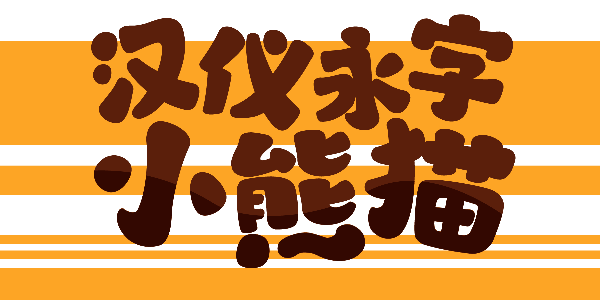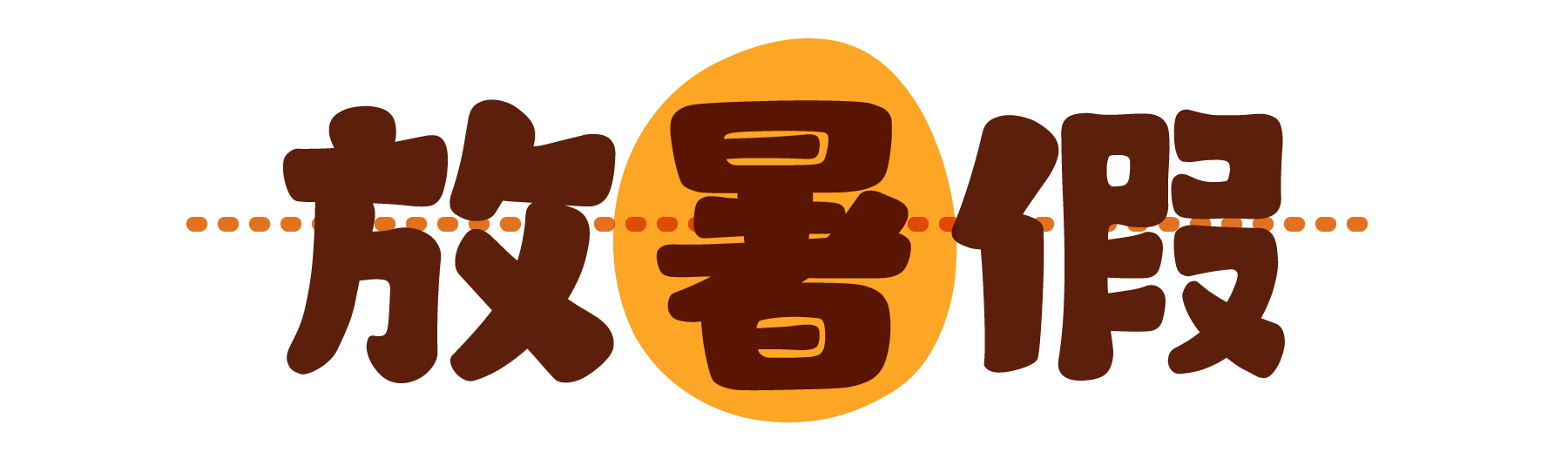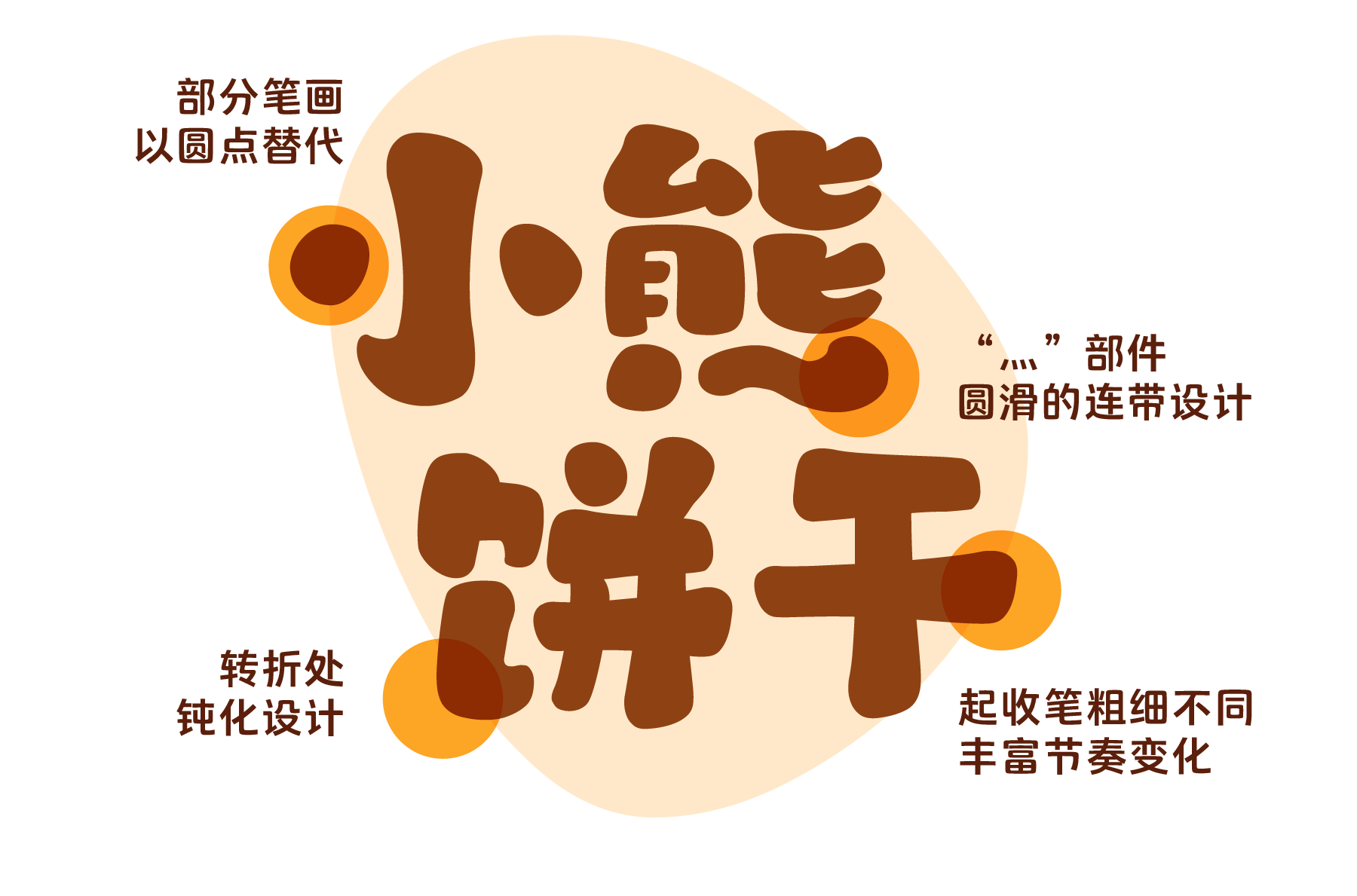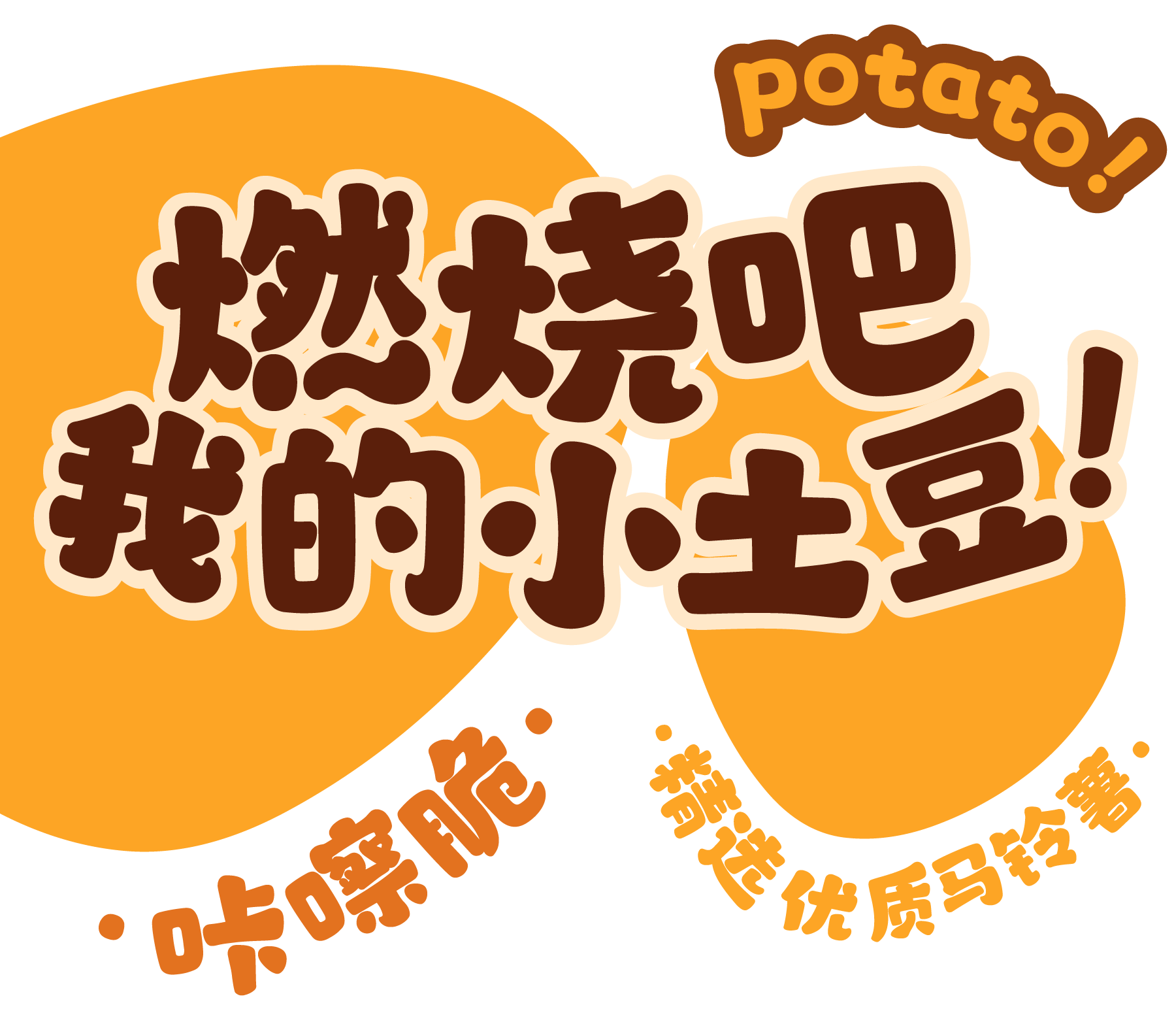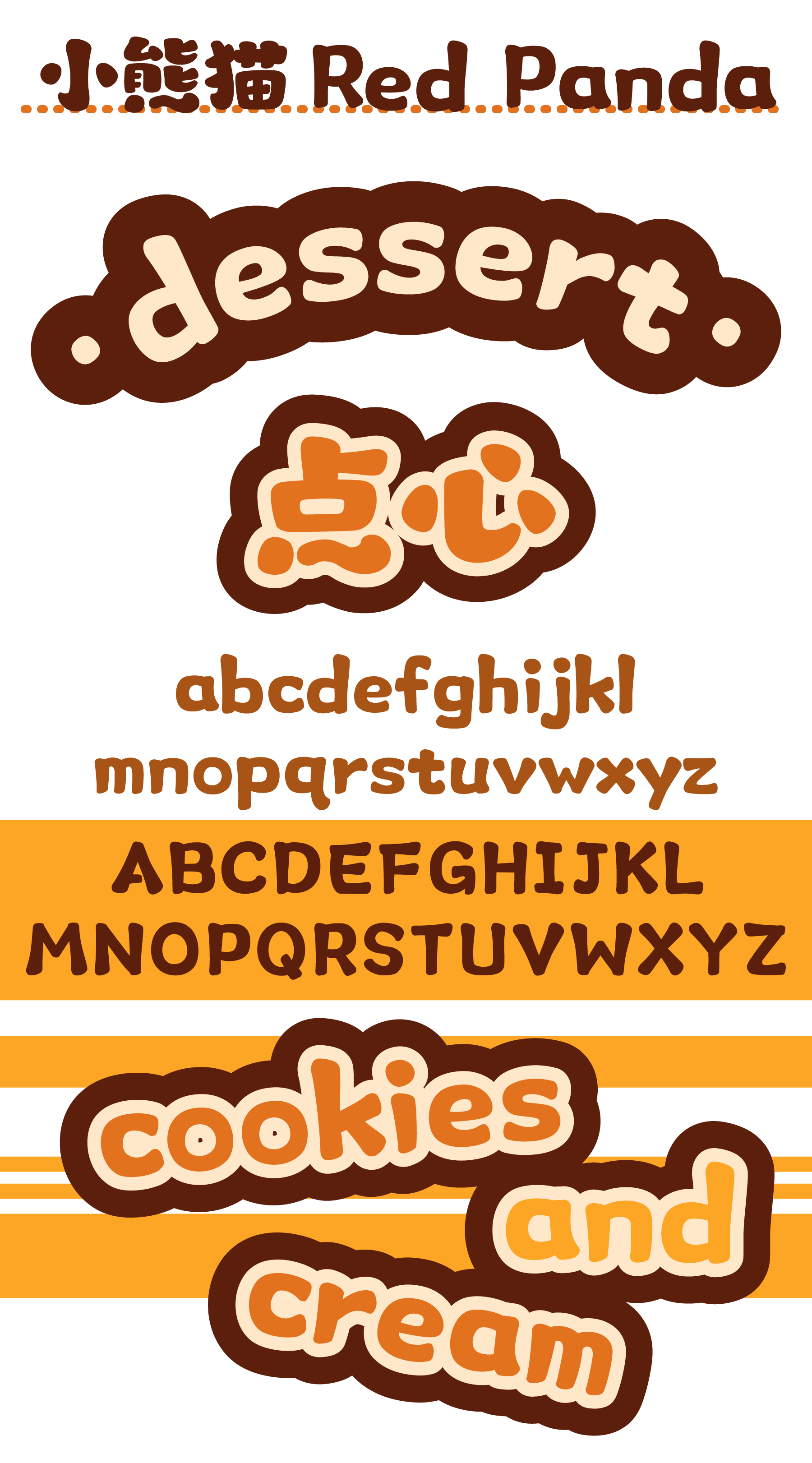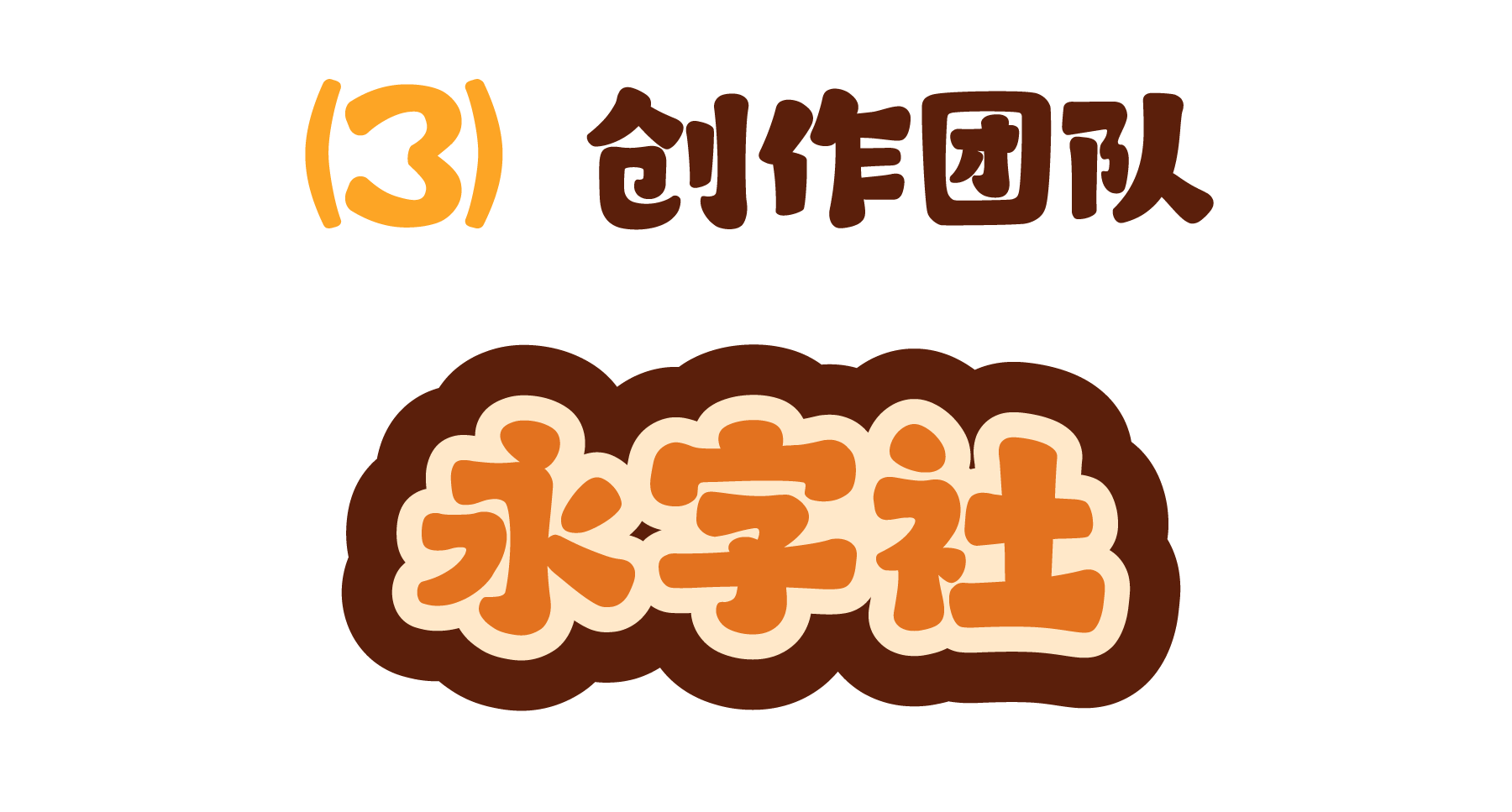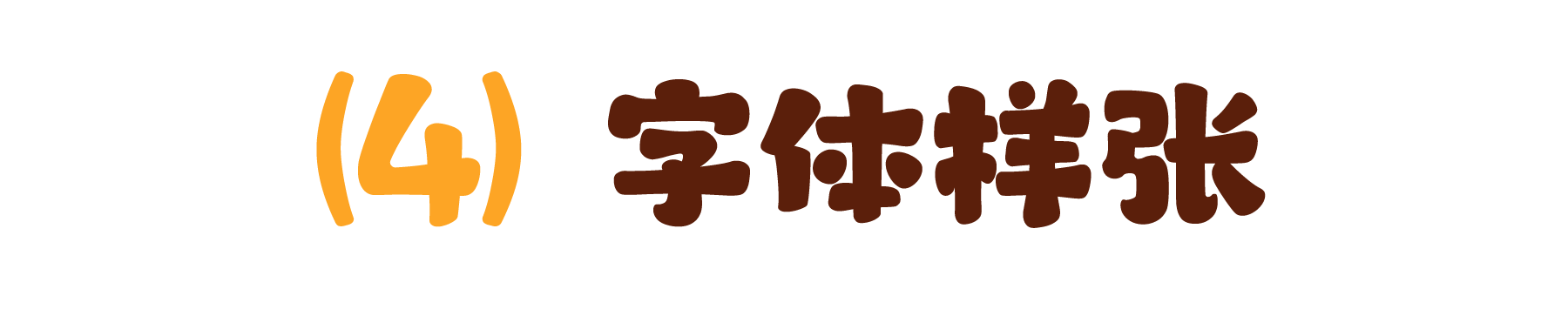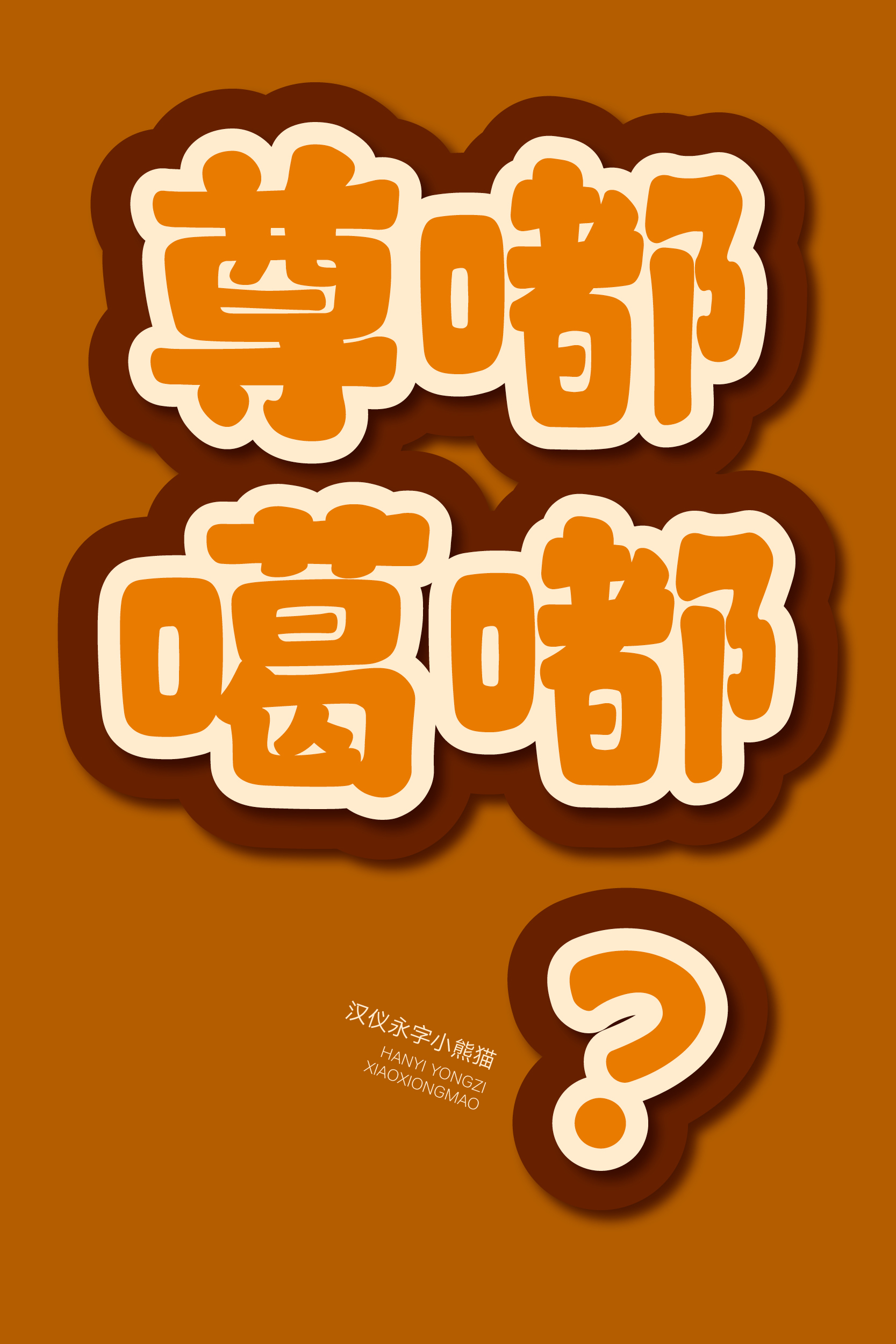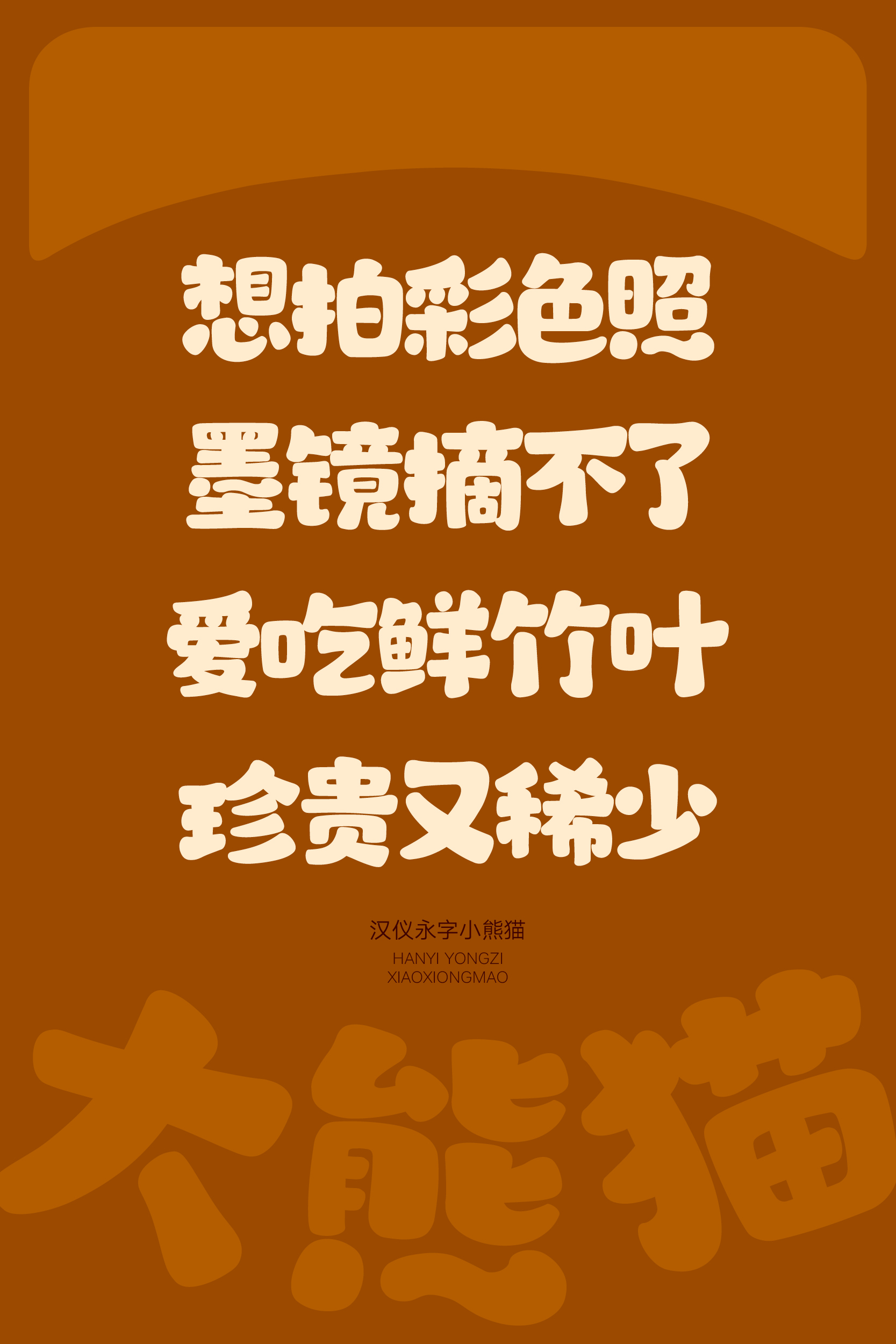
圆润可爱的小熊猫躲进字体里了
汉仪永字小熊猫,来自永字社的一款设计字体。字体整体圆润可爱,字面略小、饱满充实,圆头圆尾的笔画柔软有弹力,给人以轻松快乐的视觉体验。笔画有粗细变化,化方为圆,并加入一些圆滑的连带,自然稚拙,像是小熊猫用掌垫绘写而成。这款字体适合用于少儿科普、图书绘本、食品包装、休闲娱乐等使用场景,为排版创造可爱活泼、柔软温暖的氛围。
整体圆润可爱,字面略小,饱满充实,风格可爱活泼,有童趣。
圆头圆尾的笔画柔软有弹力,像是小熊猫用掌垫绘写而成,给人以轻松快乐的视觉体验。粗细结合、恰到好处的笔画设计,解决了字内空间拥挤而容易造成字体本身的识别度。
软乎乎的笔画能迅速拉近彼此距离,营造出可爱活泼、柔软温暖的氛围,适合用于少儿科普、图书绘本、食品包装、休闲娱乐等使用场景。
汉仪永字小熊猫的西文部分同样有着圆润可爱的造型,圆头圆尾,与中文部分呼应匹配。